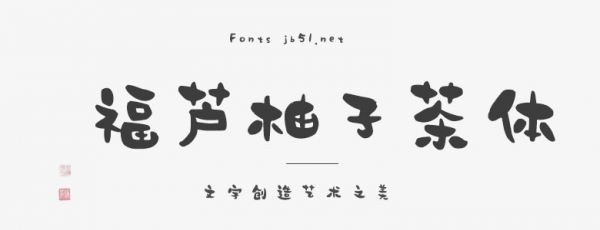
這款柚子茶字體,旨在用視覺(jué)傳遞柚子茶的獨(dú)特魅力。字體采用古樸又靈動(dòng)的手寫(xiě)風(fēng)格,筆畫(huà)圓潤(rùn)且富有變化,恰似柚子果肉的飽滿(mǎn)與柔軟,通過(guò)字體設(shè)計(jì)表達(dá),展現(xiàn)出柚子茶的自然純粹 。筆畫(huà)間呼應(yīng)柚子金黃飽滿(mǎn)的筆觸營(yíng)造出溫馨、誘人的氛圍,讓消費(fèi)者看到設(shè)計(jì)時(shí),就能在腦海中浮現(xiàn)出柚子茶的香甜,產(chǎn)生品嘗的欲望。